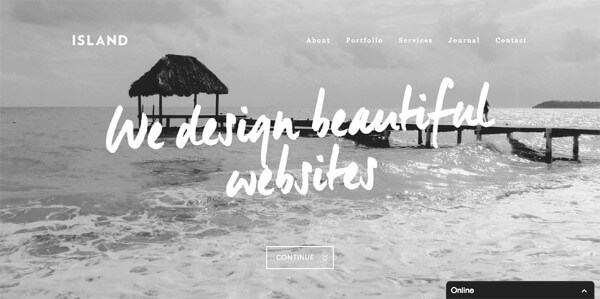
「親しみ」表現だけじゃない!【手書き風フォント】を使ったWebデザインのアイデア集
以前ご紹介した「2016年に支持されたタイポグラフィのトレンド」の記事でも「手書き風フォント」が取り上げられていました。
手書き風フォントというと、ブランドに対する「親しみやすさ」を表現するものと直感的に感じてしまいますが、事例を見るとクールでスタイリッシュな表現にも向いていることがわかります。
そんな手書き風フォントの活用法が広がるWebサイトを各シーンごとに5サイトずつご紹介していきます。
手書き風フォントを使っているWebサイト5選
1.Mint Design
mint-design
小規模専門店のブランディングとデザインを行う会社で、Webサイトの全ての文字に手書き風フォントを使っています。そのことにより、この企業が制作するWebサイトが大衆化されておらず、クリエイティビティを感じさせ、競合他社と比べて抜きん出たものとなっています。
2.Vince and Marlene
vince-and-marlene
少し変わった手書き風フォントを使い、ウェディングWebサイトをユニークで楽しいものにしています。新郎新婦のパーソナリティが輝いて見え、ウェディングがとっくに終わっているのにも関わらず、RSVPボタンを押したくなります。
(※編集註:「RSVP」は仏語で「Repondez s’il vous plait.――お返事ください」の略で、ここでは結婚式への参加意思表明のこと)
3.We Are Island
island
Island Collectiveはデザインとマーケティングのエージェントです。こちらのWebサイトには太字のメッセージが手書き風フォントで描かれています。太字にすることでメッセージがより顕著になり人々の注目を集めています。
4.Skylark English
skylark-learning
高クオリティかつ楽しい子供教育用のリソースを提供しているWebサイトです。手書き風フォントを使うことでWebサイトを楽しく見せ、また、意図したメッセージが上手く組み合わさっています。
5.Serve Seattle
serve-seattle
手書き風フォントを上手く使い、一番大切なメッセージに注目が集まるようにしています。メッセージが際立ち、Webサイト訪問者に対して強い印象を与えるでしょう。
次のWebデザインプロジェクトのための5つの手書き風フォント
1.Briella
briella
女性的なフォントで、ウェディングの招待状やバースデーカード、女性向けのビジネスのロゴ等に向いています。
2.Simplicity
simplicity
名前の通りとてもシンプルなフォントです。アクセントフォントとして有効で、特にナビゲーションメニューやヘッダーなどへの使用がおすすめです。
3.Little Wonder
little-wonder
ディスプレイフォントとして使うのに十分な太字です。ヘッドライン、ポスター、Webサイトトップ画像との組み合わせなどで使うのに適しています。
4.Clarkson
clarkson
レトロな雰囲気のフォントです。アンティークショップやハンドメイド品を販売しているお店など、ヴィンテージ、レトロなイメージを持ちたいWebサイトにぴったりです。
5.Drustic Dialy
druistic-dialy
こちらもレトロな雰囲気のフォントです。太字であるため、ポスター、ロゴ、訪問者の目を引きたい箇所への使用をおすすめします。
まとめ
「手書き風フォント」と言っても、多様な用例・表現手法があることがわかりますね。ロゴタイプのアイデアのひとつとしてストックしておいてはいかがでしょうか。
(※本稿は「Using Handwritten Typography in Web Design」を翻訳・再編集したものです)